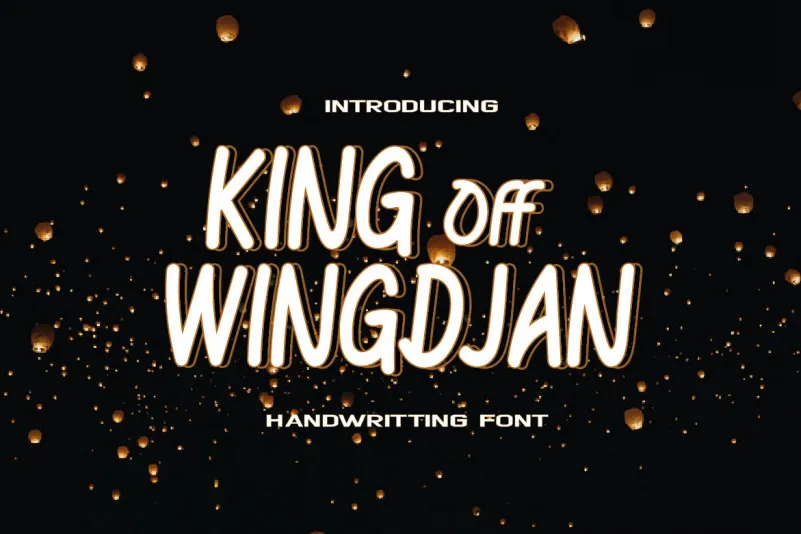
KING Off WINGDJAN Font – Download Grátis
A fonte ‘KING Off Wingdjan Font’ está ideal para quem busca uma escolha única para adicionar um toque pessoal a seus projetos digitais. Este é um tipo de escrita feita à mão com uma textura suave e encantadora, perfeito para criar cartas de noivado, anúncios, logotipos, citações ou qualquer projeto que busque uma sensação romântica e pessoal. Se você está procurando por uma fonte deslumbrante e única para suas criações digitais, a ‘KING Off Wingdjan Font’ é um ótimo lugar para começar. Suas texturas elegantes e sua maneira de brilhar com diferentes tonalidades garantem que seu design seja memorável e sofisticado. Esta fonte foi projetada pela Design Amour e pertence à categoria Playful Fonts, oferecendo uma paleta vibrante e divertida para aqueles que gostam de adicionar um toque animado a suas criações digitais. Seja para criar cartas personalizadas ou logotipos memoráveis, essa fonte será seu parceiro perfeito em sua jornada criativa.